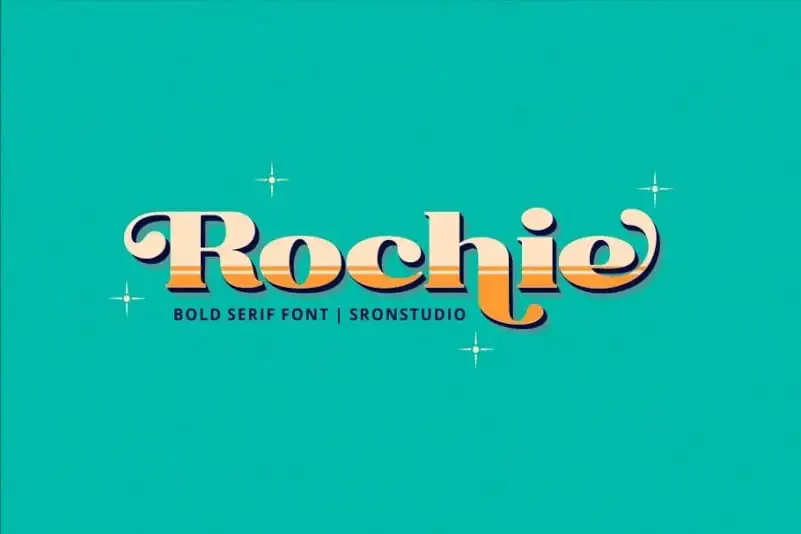
A Rochie Serif Font é uma tipografia serif vintage com traços grossos projetada para oferecer mais escolhas aos designers. Este tipo de letra perfeito para diversas aplicações, incluindo identidade empresarial, convites, design de embalagens, criação de produtos, etiquetas e até mesmo fotografias e marcas digitais. Ideal tanto para eventos especiais como posts no Facebook ou Instagram, a Rochie Serif é uma opção versátil que vai agradar os criativos buscando um charme elegante em seus projetos. Composta por traços bem definidos e características familiares, esta fonte traz ao seu projeto uma aparência sofisticada e vintage sem perder sua funcionalidade prática, tornando-se uma escolha ótima para quem procura um toque de elegância em qualquer design.